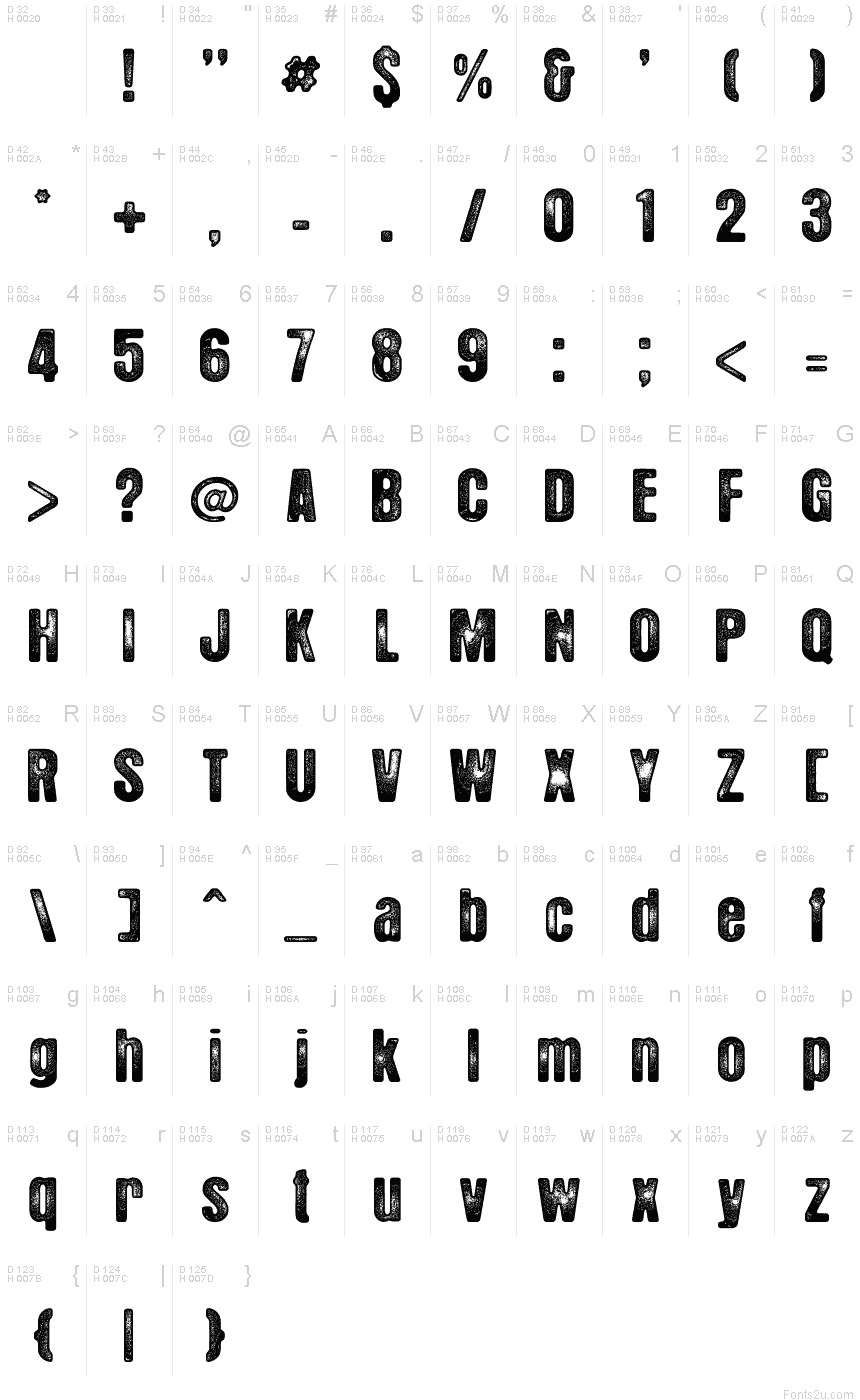
Hotel Coral Essex
Hotel Coral Essex od Pennyzine to darmowy, erodowany krój displayowy, który wygląda, jakby został zdjęty prosto z wyblakłego od słońca szyldu motelu. Masywne, zaokrąglone litery są „zjedzone” przez ziarniste kropki i poszarpane krawędzie, co nadaje każdemu słowu zużytą, wyczuwalną teksturę – niczym zardzewiały metal czy łuszcząca się farba. Jest odważny, głośny i natychmiast buduje nastrój rozkładu, nostalgii lub energii punkowego lo-fi.
Dzięki Hotel Coral Essex nadasz więcej charakteru plakatom koncertowym w stylu grunge, tytułom horrorów, fanzinom, okładkom albumów, markom deskorolkowym, grafikom streetwearowym i postarzanym opakowaniom. Nieregularna erozja sprawia, że tekst pozostaje wyrazisty w większych rozmiarach, a węższe odstępy pomagają budować gęste, uderzające logotypy. Połącz ten darmowy font z czystym, neutralnym bezszeryfowym krojem w tekście głównym, aby utrzymać chaos tam, gdzie to ważne: w nagłówkach.